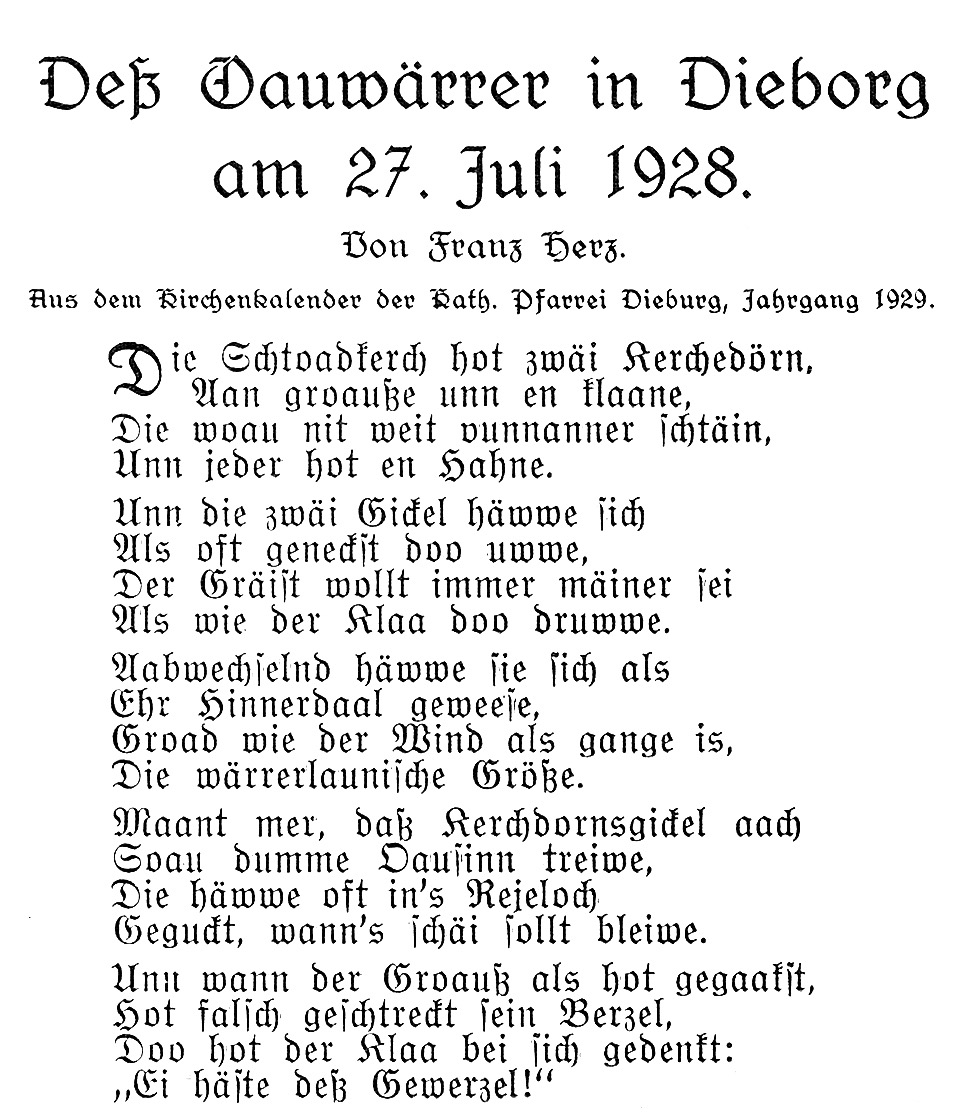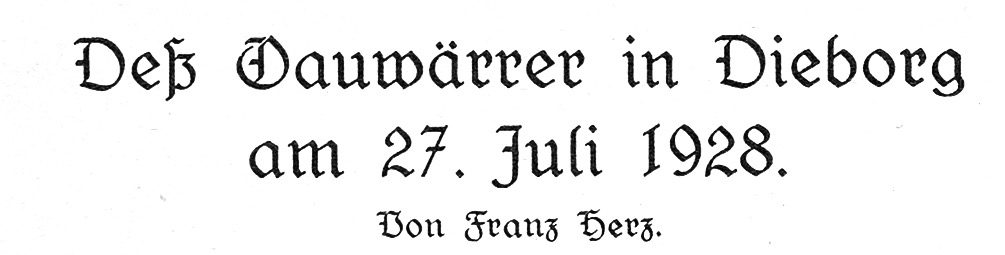
Schriftfont, der in den Jahren um 1930 verwendet wurde. (Deß Oauwärrer in Dieborg)
Ich habe hier ein kleines Büchlein, das 1931 gedruckt wurde. Ich suche nun den Schriftfont, der hier verwendet wurde. Ich vermute, dass es eine Schwabacher-Font ist. Aber welcher genau, konnte ich bisher nicht heraus finden und erhoffe mir Hilfe von diesem Forum. Mit freundlichen Grüßen Hans Rohmann
Gelöst von Erwin Krump
Es ist die „Eleonore“ aus dem Jahr 1913 von der „Actiengesellschaft für Schriftgießerei und Maschinenbau, Offenbach/Main“.
Hallo, möchte mich nochmal melden. Ich habe jetzt eine kleine Textpassage gescannt. Könnte es sein, dass es da sich um verschiedene Schriftfont handelt?
Das Gedicht ist im Dieburger Dialekt geschrieben.
Was mir auffällt ist, dass z. B. das "H" im Gedichttext anders aussieht, als in den genannten Fonts. Scheint ein anderer Font zu sein.
Die Gedichttext-Fraktur könnte die „Anker Schul-Fraktur“, Lg.-Nr. 19, 1888 (Lg.-Nr. 20, 1900, sieht ein wenig anders aus) oder die „Schul-Fraktur, Breite“ von J. G. Schelter & Giesecke, Leipzig, sein.
Das ist ja schwieriger als gedacht, aber interessant. Die Frage ist nun, kann man von dem Font "Anker Schul-Fraktur" einen komplette Abbildung bekommen? Mit freundlichen Grüßen Hans Rohmann
Es ist einfach so, dass man Überschriften in einer der aus dem Seemann gezeigten  Kanzleischriften gesetzt wurde, die hakt regional aus der nächstgelegenen Schriftgießerei stammten, und der eigentliche Text in irgend einer der hunderten Normalfraktur-Varianten gesetzt wurde, von denen dann jede Setzerei einer ebenso von einer lokalen Schriftgietzerei kam. Siese Schriftart hat sich nahezu kaum verändert von Dürers Zeiten, dessen Bücherr in dieser S chrift gesetzt wurdee als das Arbeitspferd unter den Schriftarten bis 1941 gehalten